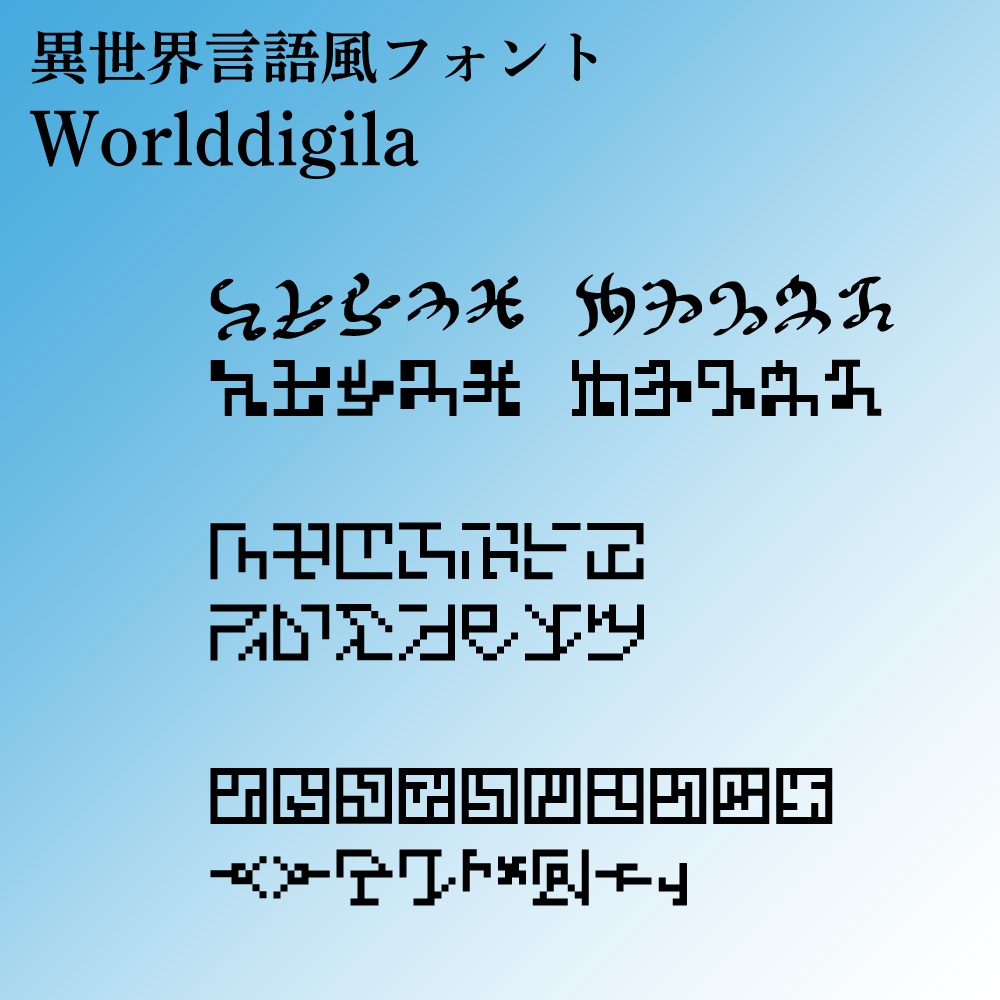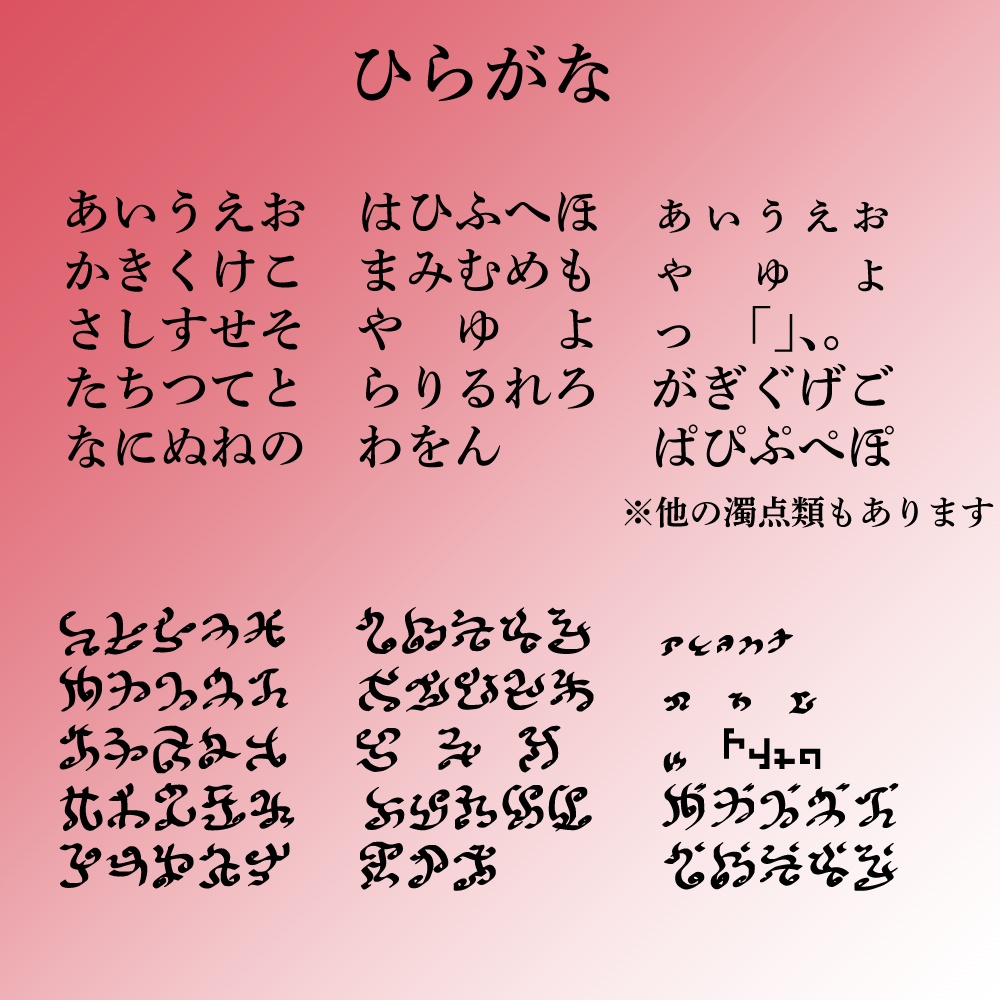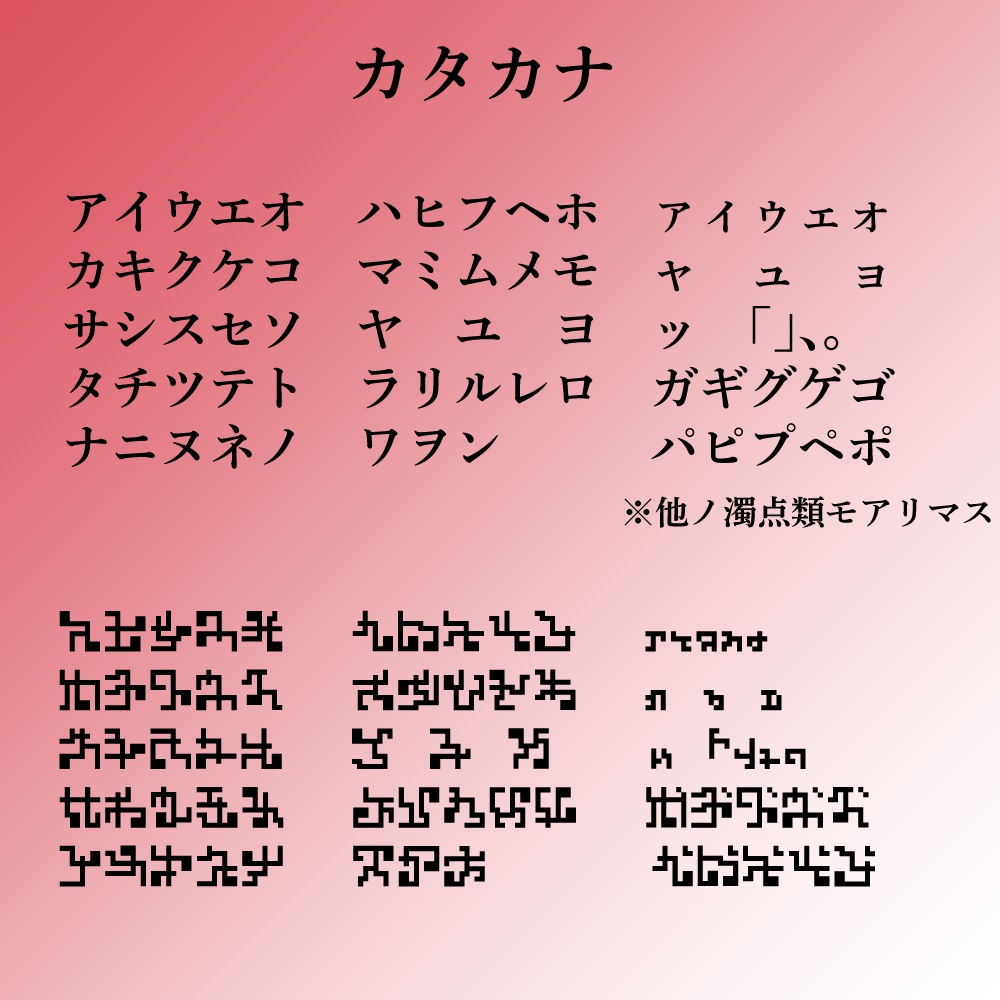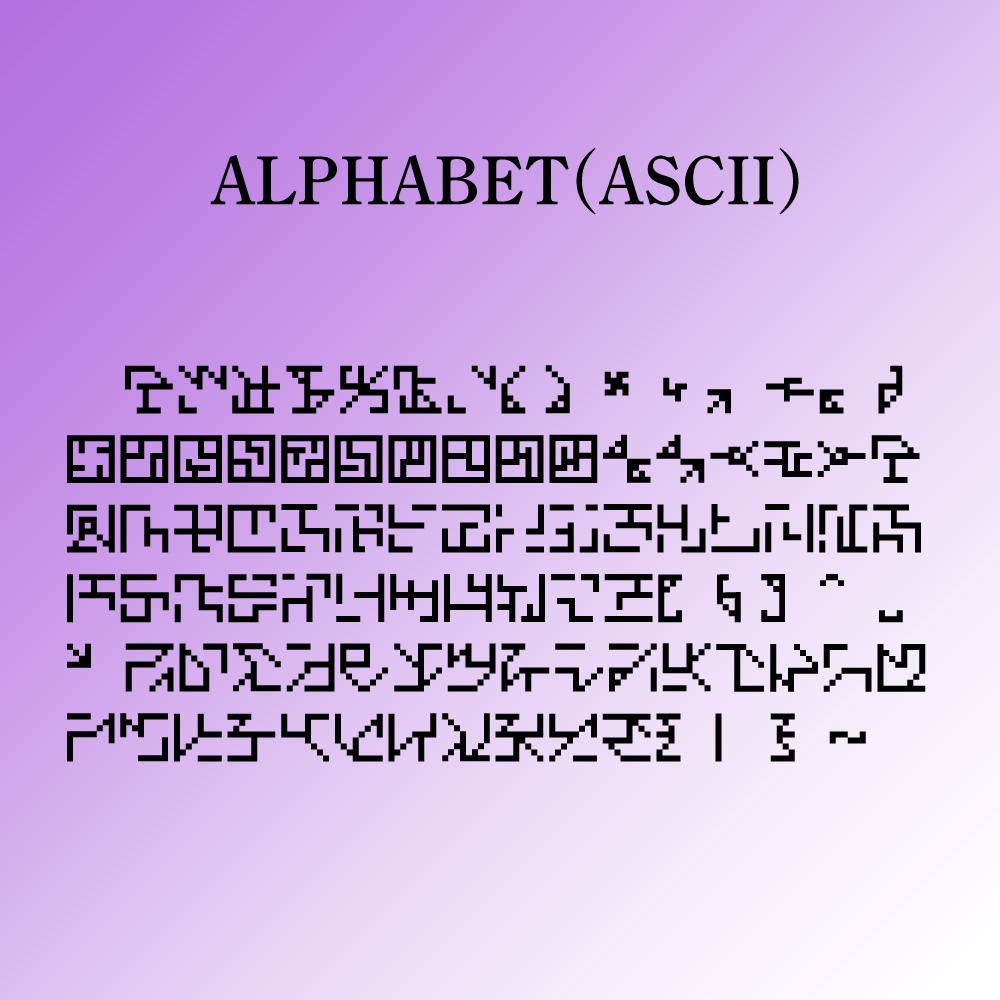
異世界言語風フォント「Worlddigila」
異世界の言語風に作成したフォントです。ひらがなは東洋の呪文風、それ以外はデジタルチックになっています。 1つのフォントで2種類以上の雰囲気が使い分けられるおいしいフォントです。 形式は.otfと.ttfに対応しています。どちらも内容は同じです。 データはzip形式で保存されていますので、解凍ののち、readmeに目を通してからご利用ください。 現在の最新版はver.1.008です。該当のzipをダウンロード後、解凍してご使用ください。 もしかするとフォントの改良や文字追加をするかもしれませんが、その場合でも現在のところ、過去データの消去や値上げは考えていません。 【使用例】 ・暗号文にする ・作品の装飾や呪文にする ・背景に忍ばせる 【収録文字】 ・半角大文字/小文字アルファベット(全角は非対応、ただしサイズはほぼ正方形) ・全角ひらがな、カタカナ ・ASCIIコード内の記号 ・他ごく一部の記号 【利用規約】 ・商用、非商用ともに利用可能です。同人への利用も自由です。 ・作者は著作権を放棄しておりません。自作発言等はご遠慮ください。 ・本フォントを利用できるのは購入された方のみです。複数人が使用する場合は人数分のご購入をお願いします。 ・本フォントを利用して発生した、いかなる損害についても作者は責任を負いません。 ・フォントデータをインストールした時点で利用規約に同意したものとみなします。 【禁止事項】 ・フォントデータの改変・複製・無断転載・再配布・販売 ・当フォントを使用した制作物、ロゴなどの商標登録、意匠登録 ・文字単体の背景素材やLINE絵文字など、本フォントの文字を主体とした作品の配布、販売、サービス提供ならびにそれに類する行為(有償、無償を問わない) 【特殊事項】 ・webフォントとしての利用やアプリケーションでの使用を希望される場合は、必ず作者までご連絡ください。 【注意事項】 ・ダウンロードデータはreadme、.otfデータ、.ttfデータで構成されています。 ・予告なしにバージョンアップを行う場合があります。 ・一部の端末、ソフトウェアでは使用できない場合があります。 ・縦書きには現在のところ対応しておりません。